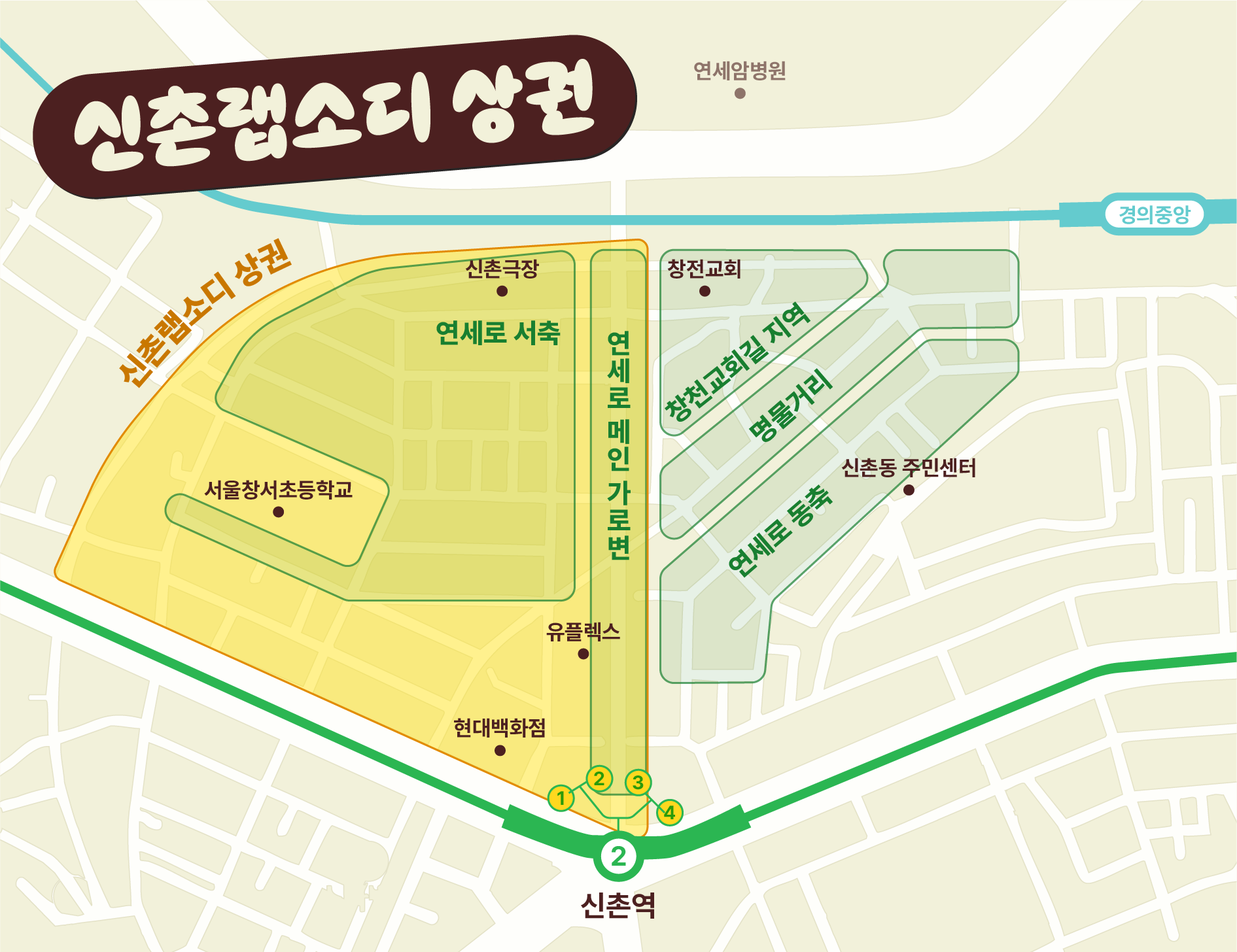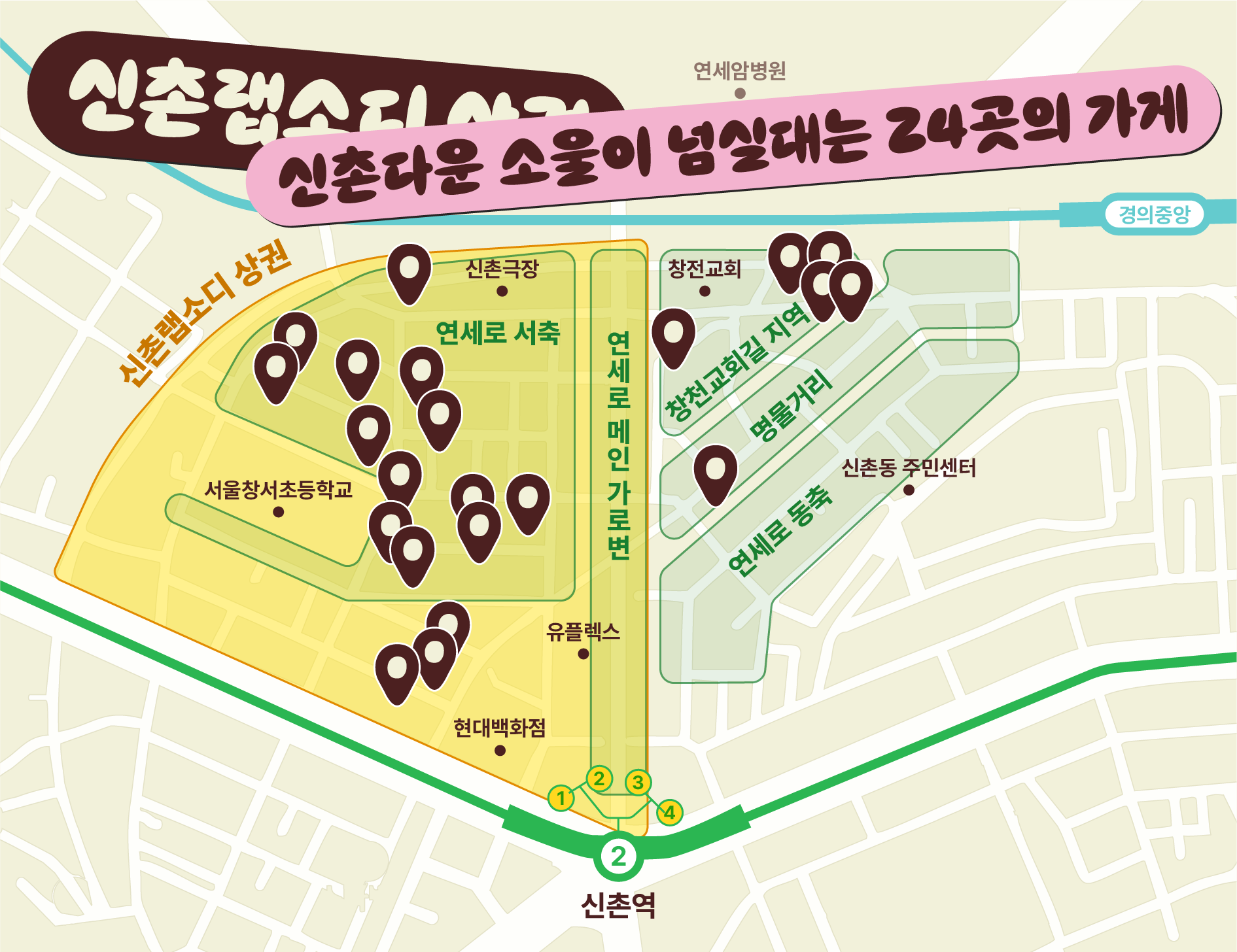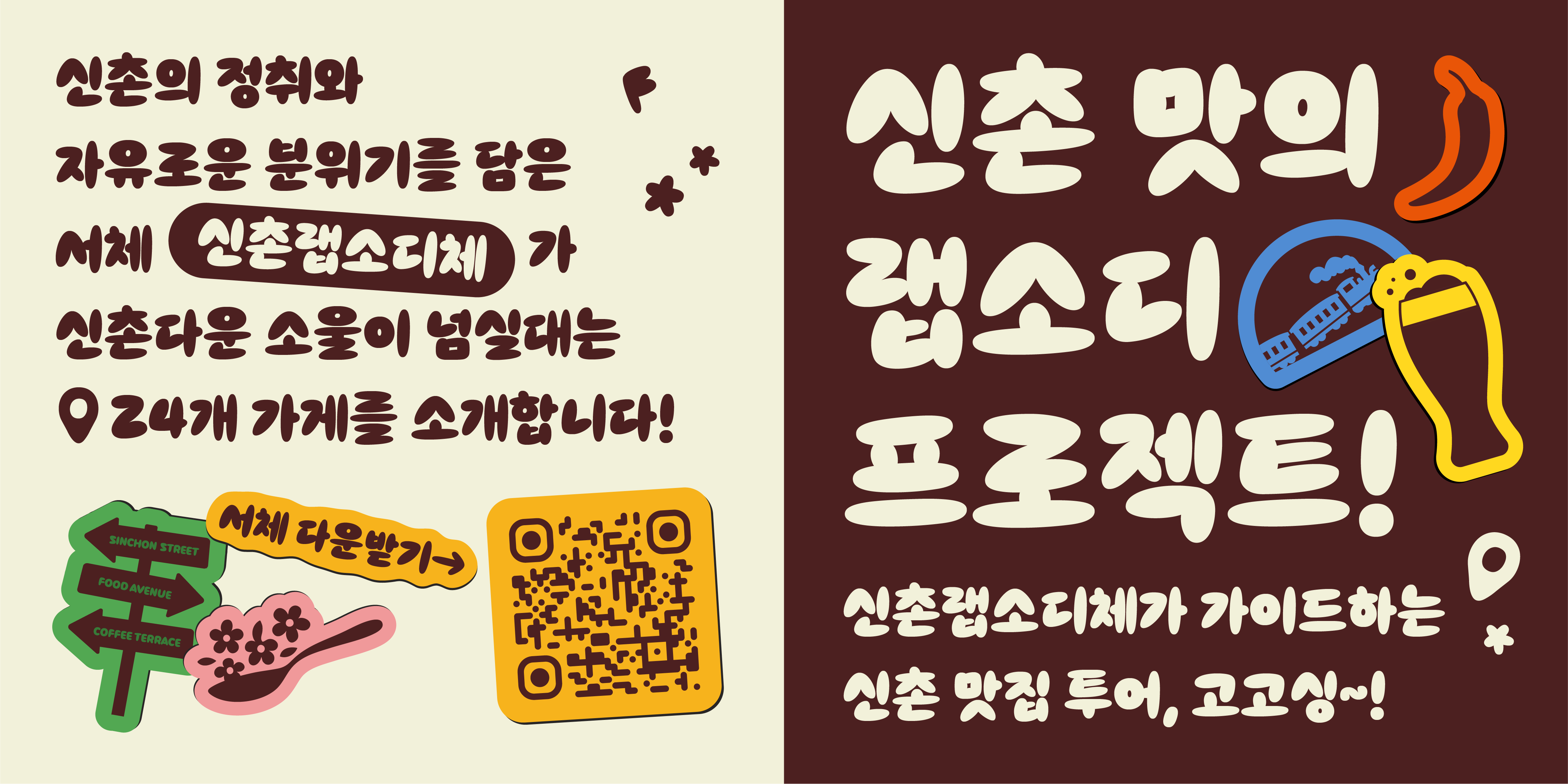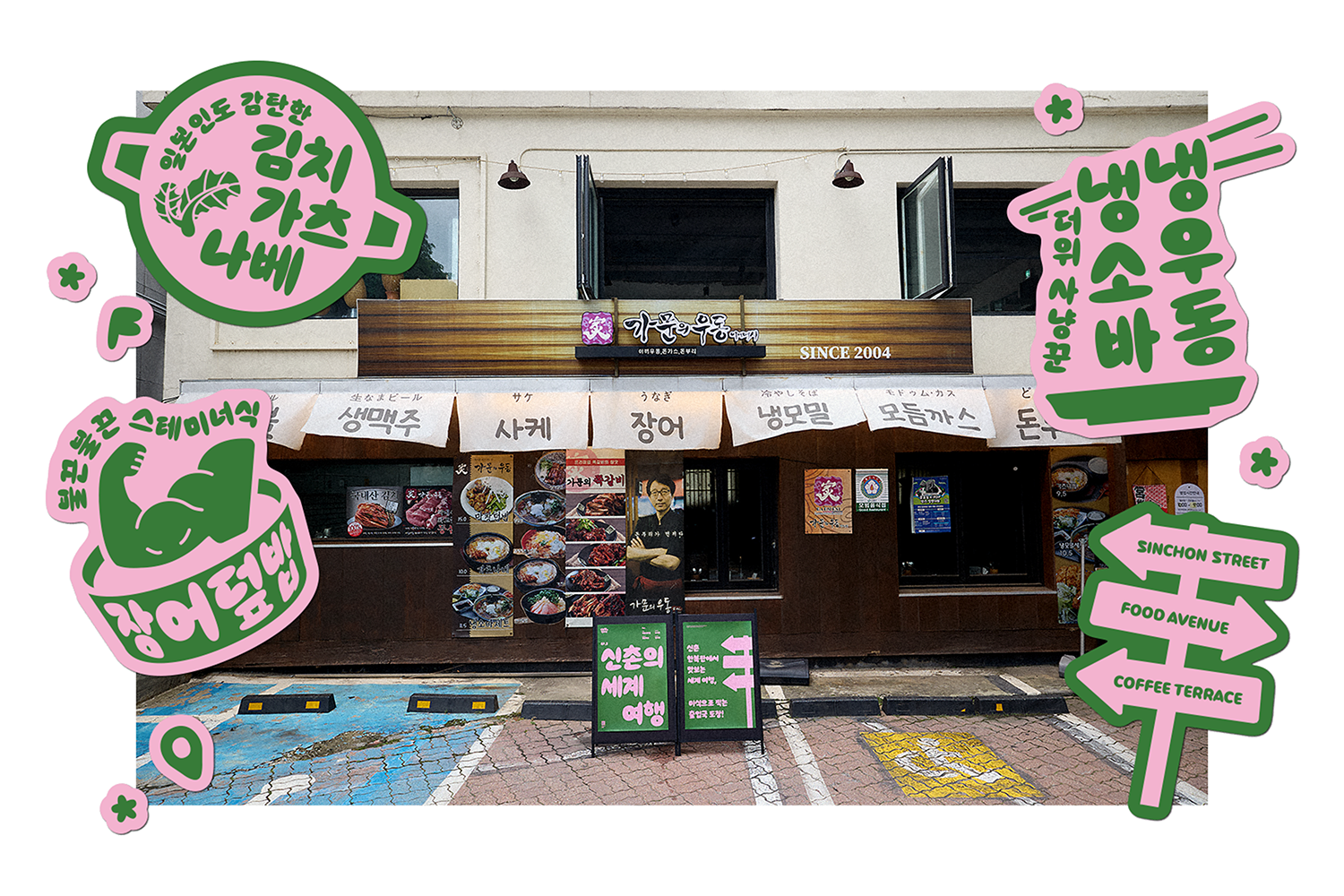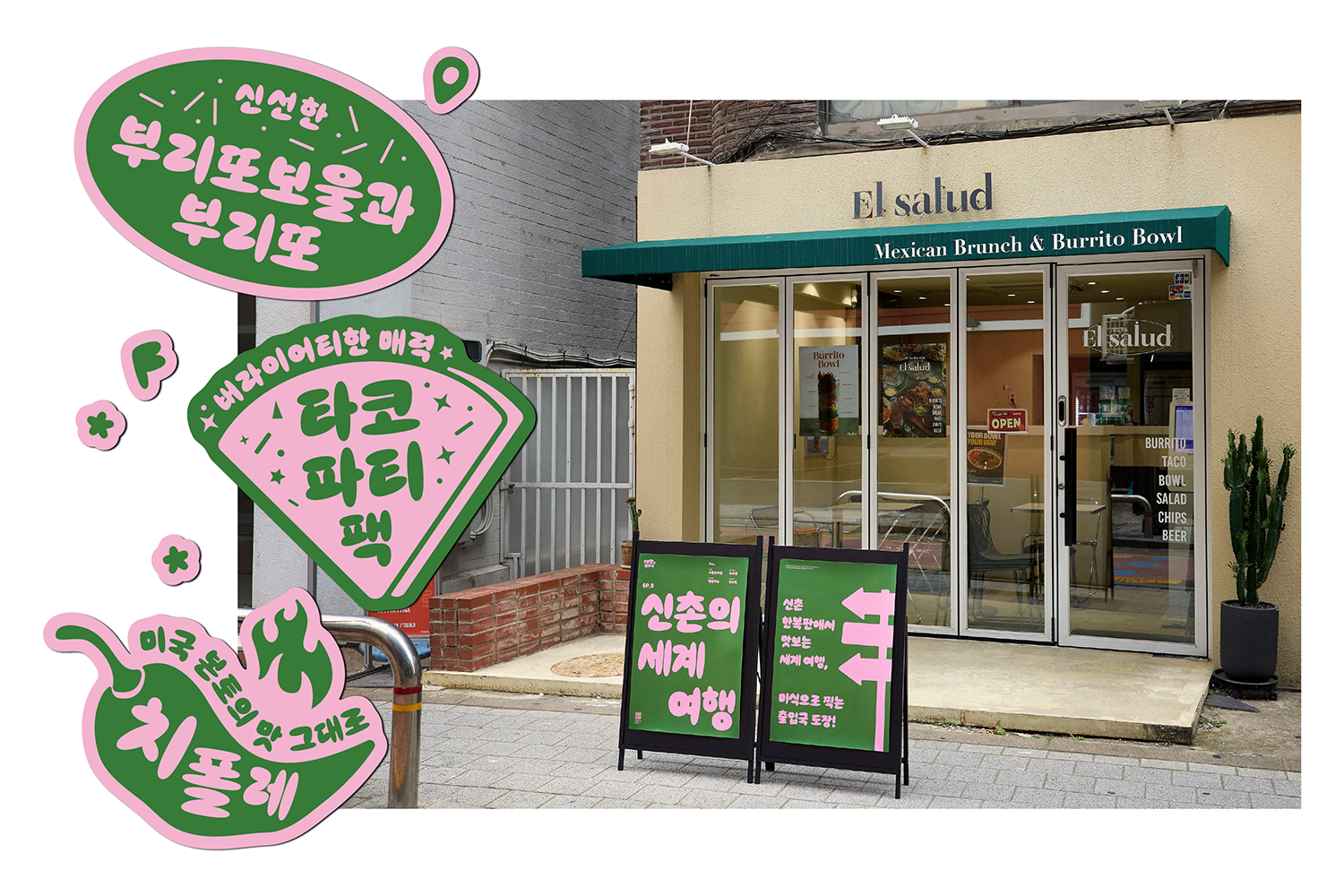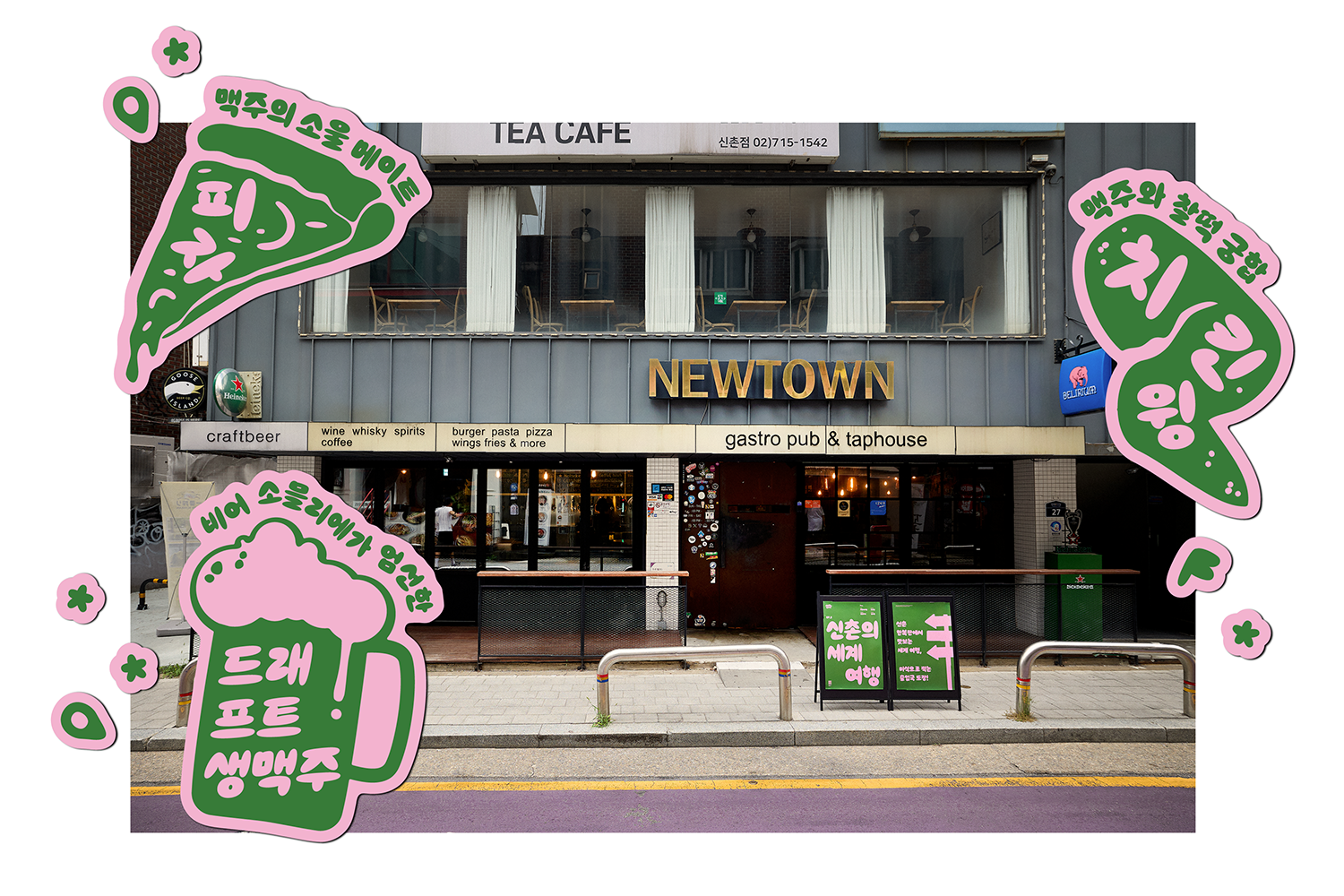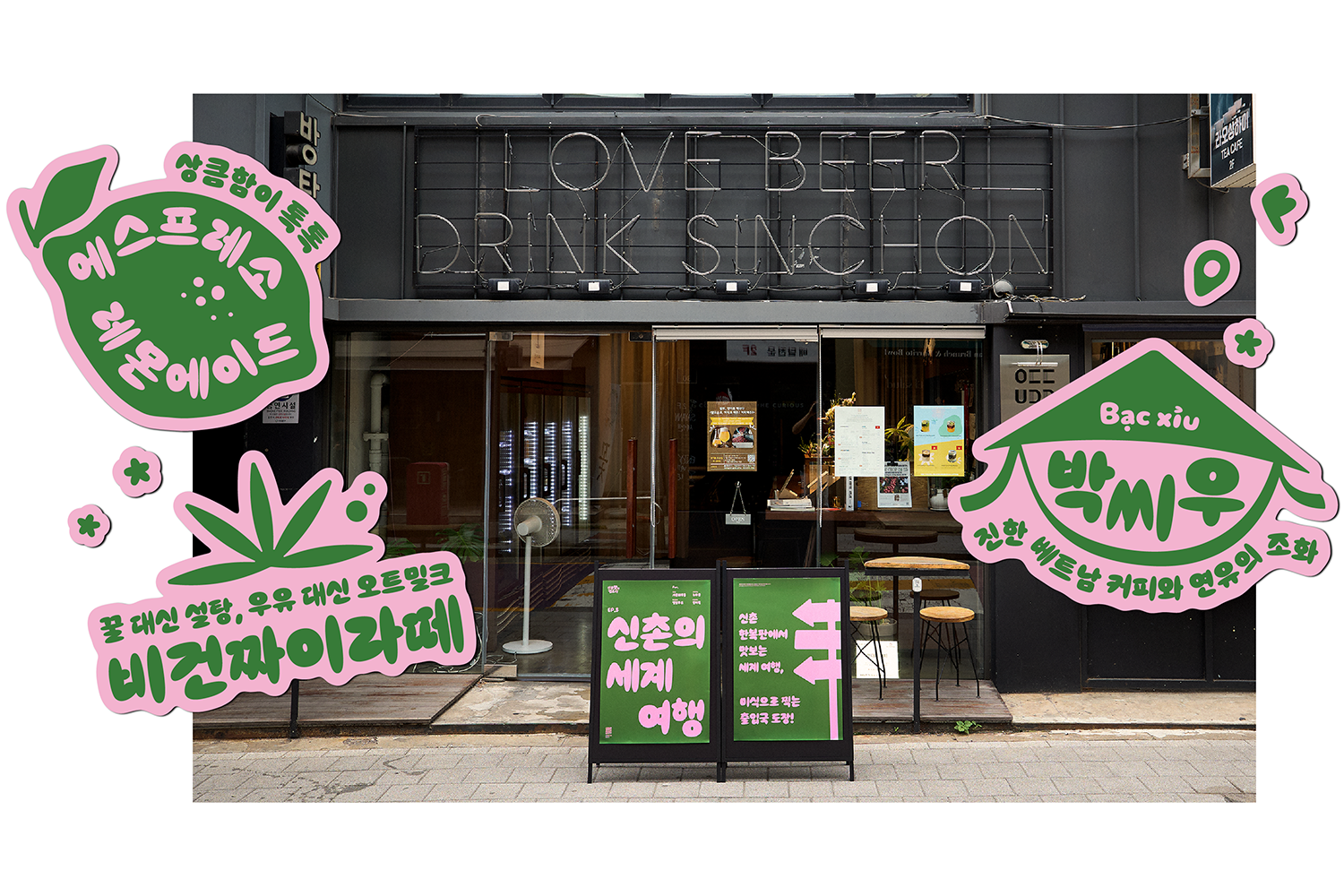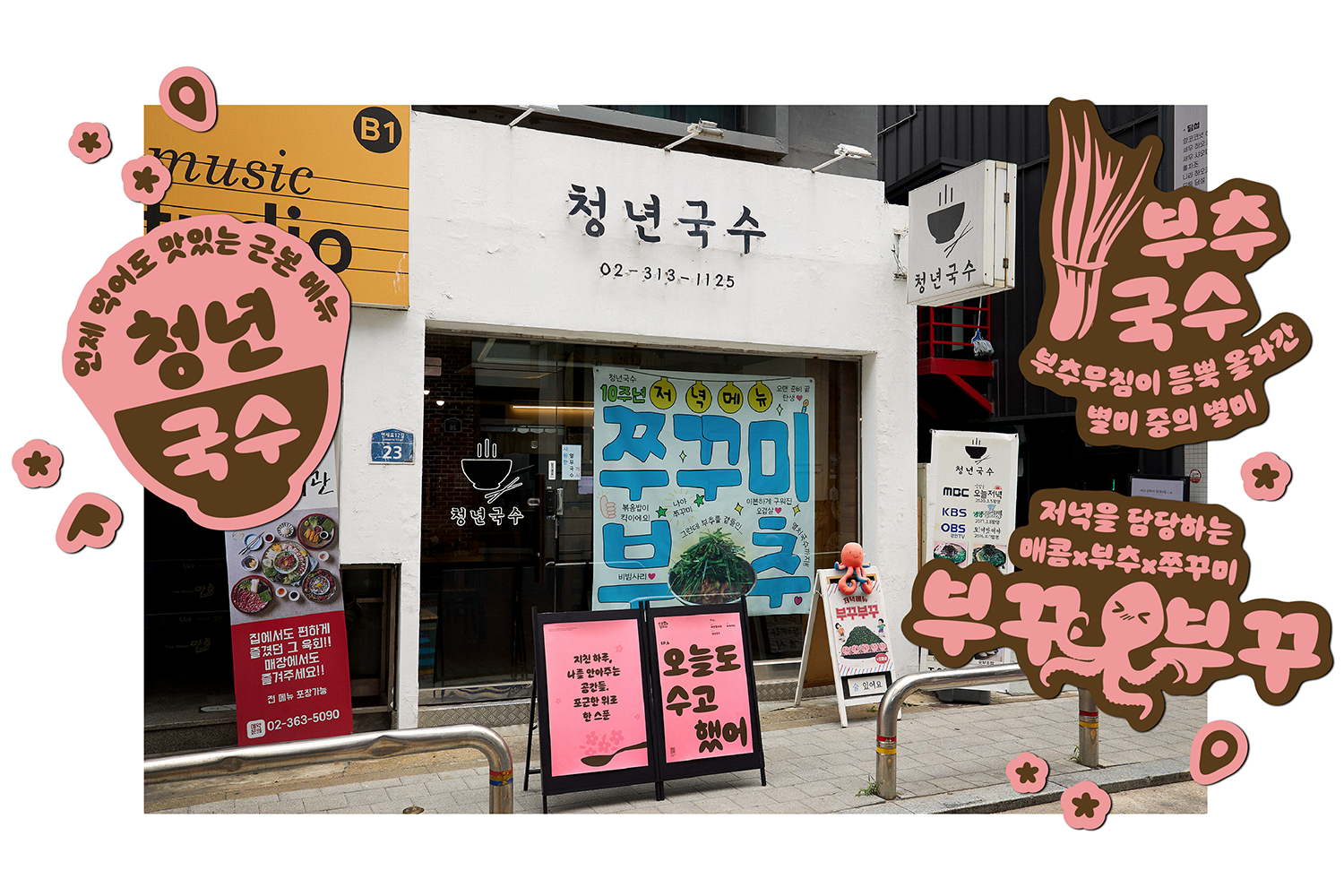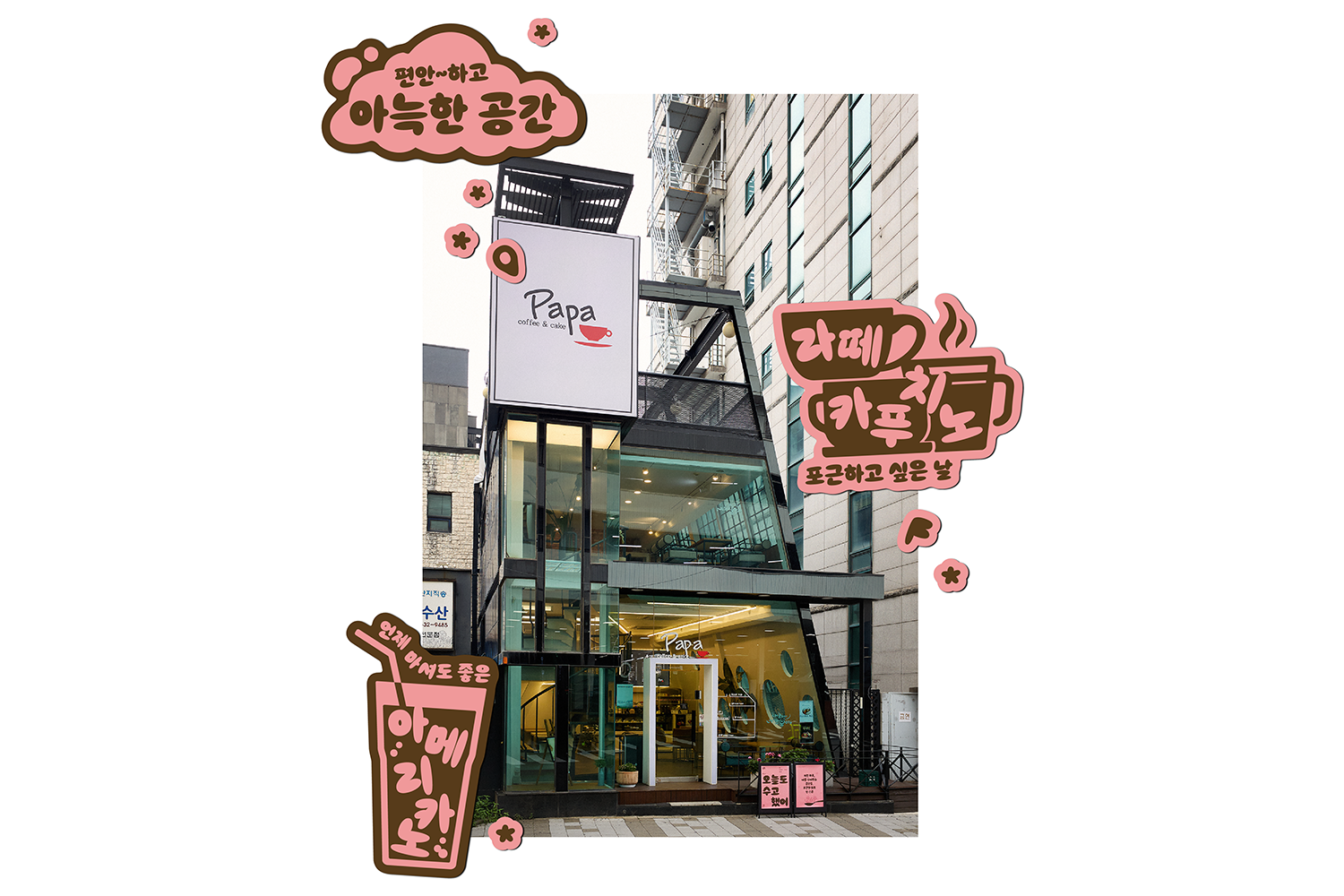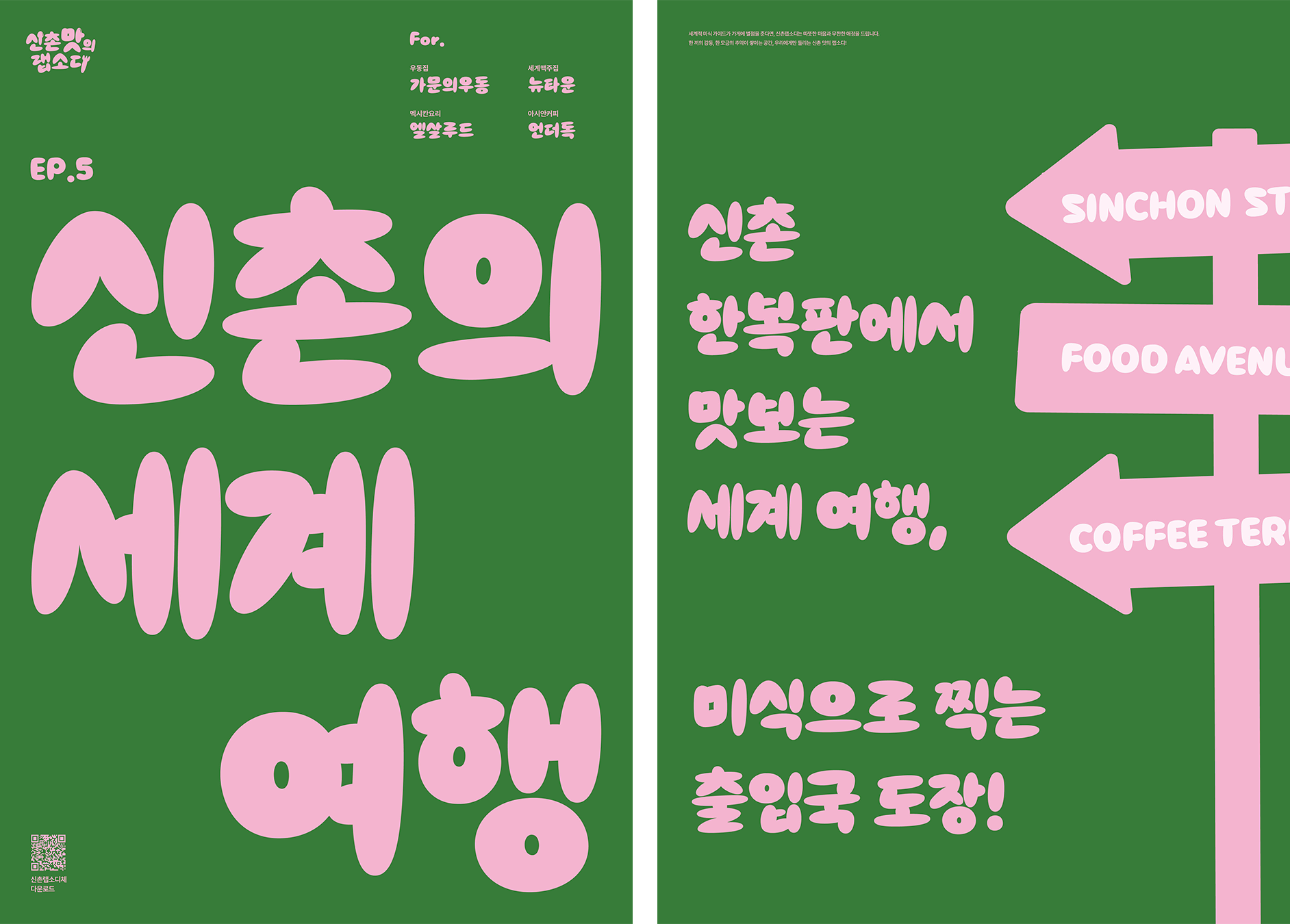
신촌랩소디체가 가이드하는 신촌 맛집 투어 시리즈 3
끝나지 않을 것만 같던 무더위의 끝자락, 세 편의 시리즈, 여섯 개의 테마로 예정되어 있던 [신촌맛의랩소디 프로젝트: 신촌랩소디체가 가이드하는 신촌 맛집 투어]도 어느덧 마지막 여정에 다다랐습니다. 오늘 소개할 두 가지 테마 속 가게들은 특히 ‘투어’ ‘여행’이라는 단어와 참 잘 어울리는데요. 먼저 신촌랩소디 상권에서 만날 수 있는 이국의 맛들을, 이어서 나의 고단했던 하루를 조용히 안아주는 따스한 소울 플레이스를 소개해보겠습니다.
신촌랩소디체가 가이드하는 신촌 맛집 투어 시리즈 3
:  EP 5. 신촌의 세계 여행, 이국의 맛 & EP 6. 오늘도 고생했어, 소울 플레이스
삼복더위라는 말이 있죠. 어느덧 여름의 막바지, 초복, 중복, 말복으로 연결되는 무더위의 나날 속에서 맛있는 음식도 많이 드셨나요? 과거에는 복날이면 영양 보충을 위해 삼계탕, 수박, 복숭아 등 영양식을 주로 먹었지만, 영양 과잉의 시대라 불리는 요즘에는 하루쯤 채식을 하며 복날을 더 가볍게 보내는 사람들도 많다고 합니다. 반면 닭 중의 최고는 치킨이지! 하며 3일의 복날 모두 치킨 배달량이 급증하기도 한다는데요. 음식이 더 많고 다양해진 만큼, 날씨의 양상과 계절의 경계가 과거와는 완연히 달라진 만큼, 특정 시간을 잘 보내기 위한 음식도 내가 직접 정하는 게 더 의미 있을 거라는 생각이 드는 요즘입니다.
끝나지 않을 것만 같던 무더위의 끝자락, 세 편의 시리즈, 여섯 개의 테마로 예정되어 있던 [신촌맛의랩소디 프로젝트: 신촌랩소디체가 가이드하는 신촌 맛집 투어]도 어느덧 마지막 여정에 다다랐습니다. 오늘 소개할 두 가지 테마 속 가게들은 특히 ‘투어’ ‘여행’이라는 단어와 참 잘 어울리는데요. 먼저 신촌랩소디 상권에서 만날 수 있는 이국의 맛들을, 이어서 나의 고단했던 하루를 조용히 안아주는 따스한 소울 플레이스를 소개해보겠습니다. 혼자서든, 누군가와 함께든 오랫동안 기억에 남을 ‘신촌의 순간’들, 치열한 여름을 보낸 여러분 앞에 선물처럼 잔잔히 띄워봅니다.
복습하기 하나. 신촌랩소디 상권은?
연세로를 중심으로 펼쳐진 ‘신촌랩소디 상권’은 신촌의 오래된 골목과 개성 있는 가게들이 모인 곳입니다. 문화, 예술, 낭만, 젊음이 공존하는 이곳은 신촌만의 감성을 고스란히 전달합니다.
복습하기 둘. 신촌랩소디체는?
‘신촌랩소디체’는 신촌의 정취와 자유로운 분위기를 담은 서체입니다.
활기와 낭만이 공존하는 신촌의 거리처럼, 다채로운 리듬과 이야기를 글자에 담았습니다.
[EP 5. 신촌의 세계 여행, 이국의 맛]
“신촌 한복판에서 맛보는 세계 여행, 미식으로 찍는 출입국 도장!”
이번 에피소드의 테마는 여권 없이 떠나는 미식 여행입니다. 신촌랩소디 상권 골목골목, 놀라운 이국의 맛들이 숨겨져 있기 때문인데요. 그 놀라움이 어느 정도냐 하면! 한 끼 한 끼 먹으며 미식의 세계 지도를 그려볼 수 있을 정도랍니다. 오늘은 일본, 내일은 멕시코, 모레는 베트남! 출출함을 안고 떠나는 신촌 속 세계 여행, 지금부터 시작합니다.
첫 번째 여행지는 일본입니다. <가문의 우동>은 신촌에서 따스한 미소를 전파하는 일식 전문점인데요. 그만둔 알바생이 친구, 가족을 데리고 꾸준히 방문하기도 하고, 단골이던 학생이 결혼해 반려자와 아이들을 데려오기도 하는,  한번 발을 들이면 좀처럼 끊어낼 수 없는 마성의 공간입니다. 간단한 인터넷 리뷰에도 미담에 넘쳐나지만, 사장님은 그 모든 게 그저 고객님들 사랑에 보답하는 일이었을 뿐이라고 말씀하시는데요. 이런 감동적인 마음에 정성 어린 메뉴까지 함께하니 치열한 신촌의 맛집 자리를 여전히 지키고 계신지도 모르겠습니다. <가문의 우동>을 대표하는 메뉴는 각기 의견이 분분하겠지만, 일단 김치가츠나베가 유명한 건 사실입니다. 개업 이후 100만여 개가 판매되었고 일본인들도 감탄하며 먹는다고 하니 <가문의 우동>을 방문한다면 꼭 먹어봐야 하겠죠. 날씨가 더우니 냉소바, 냉우동에 스테미너식으로 유명한 장어덮밥을 곁들여도 좋습니다. 그럼에도 선택이 어려울 땐, 친절한 사장님께 슬쩍 여쭤보는 것도 좋은 방법이랍니다.
다음 여행지는 멕시코 또는 미국입니다. 바로 미국 감성의 멕시칸 요리 전문점 <엘살루드>를 방문할 차례인데요. El Salud 스페인어로 살룻(Salud)은 건강과 건배를 뜻한다고 해요. 그래서일까요? <엘살루드>는 고객의 건강을 위해 하루 두 번 신선한 재료를 준비합니다. 낮에는 부리또보울과 부리또, 샌드위치 등으로 근사한 브런치를 즐길 수 있고, 밤에는 맥주와 어울리는 타코파티팩과 함께 캐주얼한 파티를 열 수도 있죠. <엘살루드>의 킥은 바로 치폴레인데요. 미국 본토의 치폴레 맛을 그대로 재현해 감탄을 불러일으킵니다. 멕시코 음식에 익숙지 않아 무얼 시켜야 할지 고민된다면 타코파티팩을 먼저 경험해보세요. 무려 네 종류의 고기와 다양한 소스를 베이스로 나만의 타코를 만들어 먹다보면, 나만의 멕시칸 취향을 디자인하는 것도 어렵지 않을 겁니다.
<엘살루드>에서 곁들여 마신 맥주로는 살짝 부족한 느낌이 든다면, 세계로 맥주 여행을 떠날 수도 있습니다. <엘살루드> 바로 맞은편, 세계 맥주 전문점 <뉴타운>이 위치하고 있는 덕분인데요. <뉴타운>은 전문 비어 소믈리에가 운영하는 세계 맥주 전문점입니다. 엄선한 드래프트 생맥주 28종이 전문적으로 관리되어 늘 신선하고 다양한 맥주를 맛볼 수 있지요. 안주 센스 역시 탁월합니다. 맥주에 어울리는 치킨과 피자, 그리고 감자튀김, 샐러드, 크래커 등, 메뉴를 고르다 밤을 새울 지경인데요. 이토록 맥주 위주인! 맥주의, 맥주를 위한, 맥주에 의한 공간, <뉴타운>에서는 여전히 신촌을 가장 진하게 누려볼 수 있습니다.
마지막 여행지는 어디일까요? 바로 베트남입니다. 베트남 커피 전문점인 <언더독커피>가 신촌 속 세계 여행의 마무리를 담당할 텐데요. <언더독커피>는 20년 경력의 전문 바리스타가 한국에 알려지지 않은 보물 같은 베트남 커피를 엄선해 소개하는 이채로운 공간입니다. 에스프레소 대신 진한 베트남 핀 커피를 베이스로 연유를 곁들인 ‘박씨우’를 중심으로, 베트남 커피꽃꿀에 레몬 껍질을 재워 향을 입히고 레몬즙과 에스프레소를 더해 만드는 ‘에스프레소 레몬에이드’, 비건을 위해 꿀 대신 설탕, 우유 대신 오트밀크를 넣어 맛을 내는 ‘비건짜이라떼’ 등 개성 만점 커피를 통해 훌쩍 베트남에 다녀올 수 있지요. 여유로운 시간 바 테이블에 앉으면 흘러나오는 사장님의 다양한 커피 이야기와 함께, 생소한 메뉴들 속 나만의 커피 취향을 발견해보세요!
[EP 6. 오늘도 고생했어, 소울 플레이스]
“지친 하루 나를 안아주는 공간들, 포근한 위로 한 스푼”
마음의 안전지대라는 말이 있죠. 마음 놓고 아무 걱정 없이 편하게 쉬어갈 수 있는 공간을 의미합니다. 점점 더 바쁘고 고단해지는 세상, 나만의 아지트를 만들고 나 자신을 돌보는 일은 중요한데요. 신촌랩소디 상권에도 많은 이들의 고단한 마음을 꼭 안아주고 위로해주는 공간들이 존재합니다. 소박하지만 편안하고, 화려하진 않지만 따스한, 모두의 안식처를 소개할게요.
점심에는 국수로 마음을 덥혀주고, 저녁에는 매콤한 쭈꾸미를 통해 기분 전환을 책임지는 <청년국수>가 신촌랩소디 상권 소울 플레이스 1호로 선정되었습니다. 점심에는 새콤한 부추무침이 듬뿍 올라간 별미, 부추국수를 맛볼 수 있고, 저녁에는 어느새 국수 메뉴들의 인기를 초월해버린 부추 쭈꾸미 볶음 부꾸부꾸가 하루 일과에 지친 사람들을 하나둘 <청년국수>로  불러 모읍니다. 꾸준히 방문해주시는 손님들 덕분에 <청년국수>의 ‘청년’이 어느덧 아들 둘을 둔 한 집안의 ‘가장’이자 ‘아저씨’가 될 수 있었다고 말씀하시는 사장님. 그 따스한 웃음이 이제는 <청년국수>를 방문하는 청년들의 매일을 격려합니다.
매일 가도 질리지 않는 커피 한 잔의 온기, <카페파파>는 프렌차이즈 카페의 시대에도 묵묵히 고유의 색깔을 지키며 학생들의 아지트를 자처합니다. 편안한 좌석과 친절한 스태프, 맛 좋은 음료는 기본! 작품이 전시되어 마치 갤러리를 연상시키는 지하 공간과 좋은 날씨를 만끽할 수 있는 루프탑, 특별한 복층 구조는 둘러보는 것만으로 하루의 기분을 완전히 책임집니다. 붐비고 복잡한 신촌 한가운데를 벗어나 잠시 쉬어갈 수 있는 공간을 자처하는 <카페파파>. 누구나 사랑하는 신촌 속 작은 쉼터입니다.
우리는 언제 꽃을 살까요? 어버이날, 스승의날, 생일, 졸업식, 입학식 그리고 프로포즈. 기념하거나 축하할 일이 있는 날, 감사나 사랑의 마음을 전하고 싶을 때 우리의 발걸음은 꽃집으로 향합니다. 그런 소중한 시간을 함께 기념할 수 있도록 도와주는 동네 꽃집이 신촌랩소디 상권에도 있습니다. 바로 <리안플라워>인데요. 작은 공간이지만 늘 사랑스러운 의미가 담긴 싱싱한 꽃들로 가득해 구경하는 것만으로 기분이 좋아지지요. 어쩐지 메마른 것 같은 날, 특히 고생한 날. 내가 설레며 골랐던 꽃 한 송이를 나 자신에게 선물해보는 건 어떨까요? 나를 위해 꽃을 사는 일이 어색하게 느껴진다 해도 걱정 마세요. <리안플라워>가 그 어색함을 특별하고 소중한 경험으로 완성해줄 테니까요.
신촌랩소디체와 함께한 여섯 가지 테마 여행, 즐거우셨나요? 피곤하고 지치는 일상 속에서 이국의 맛을 발견하기도 하고, 낯선 공간에서 따뜻한 위로를 받기도 했던 시간이었다면 더없이 기쁠 것 같습니다. 이 여름, 신촌에서의 여행들이 오래도록 기억에 남기를 바라며, 신촌랩소디는 계속됩니다!